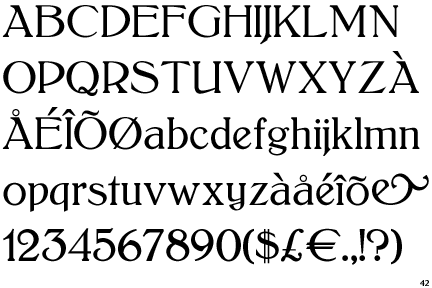
Schriftart gesucht | Briefkopf
Kann mir jemand sagen welche Schrift hier benutzt wurde?
die Schrift kenne ich nicht, tippe auf 1915 oder so. Ähnliche Auswüchse an den Serifen hat die DTL Fleischmann
Die Kleukens-Antiqua sieht sehr gut aus.
Was wächst denn dem Versal-J da aus der Seite?
Das etwas sperrige & macht dagegen keinen Hehl aus seiner Herkunft – hat was!